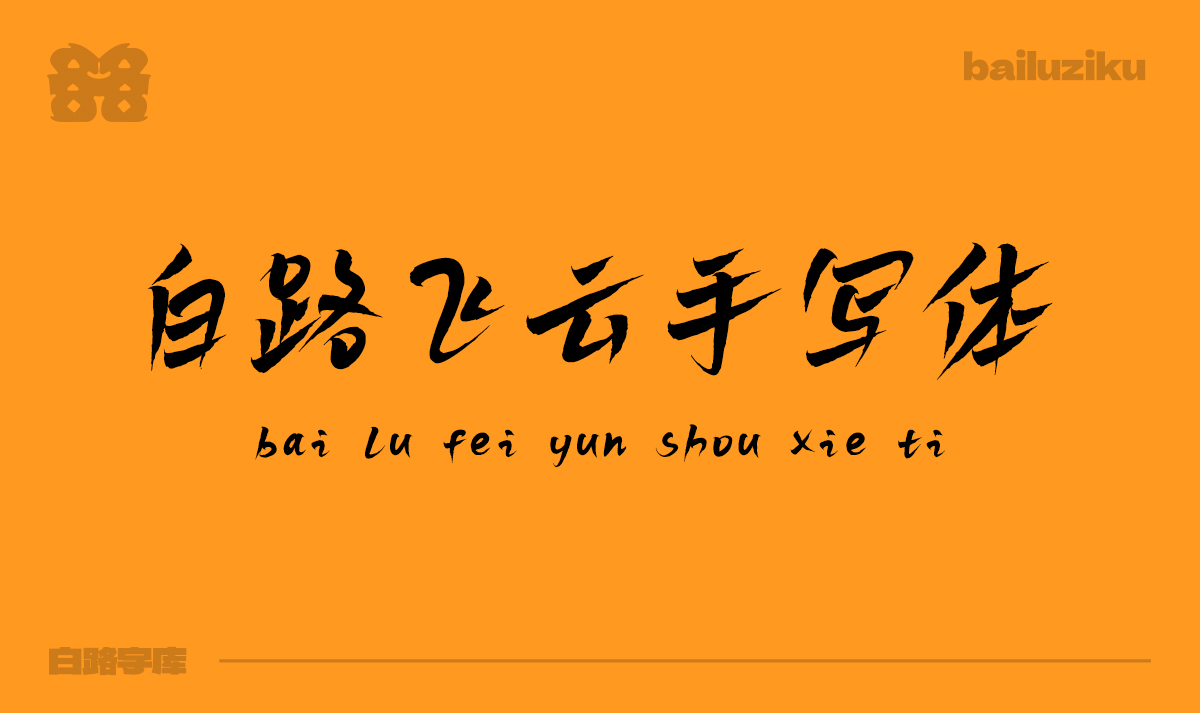
白路飞云手写体字体信息
白路飞云手写体是山人白路自己手写一款字体,字符加数字,英文及标点符号共6796个字符,该字库风格为手写偏随性飘逸,现在已正式开放免费商用,喜欢的可以下载使用。可以的话给作者打个赏,请白路兄喝杯奶茶吧!
“白路飞云手写体”是一款书写很新颖的字体,字体大方,适合各种设计作品使用!欢迎下载!